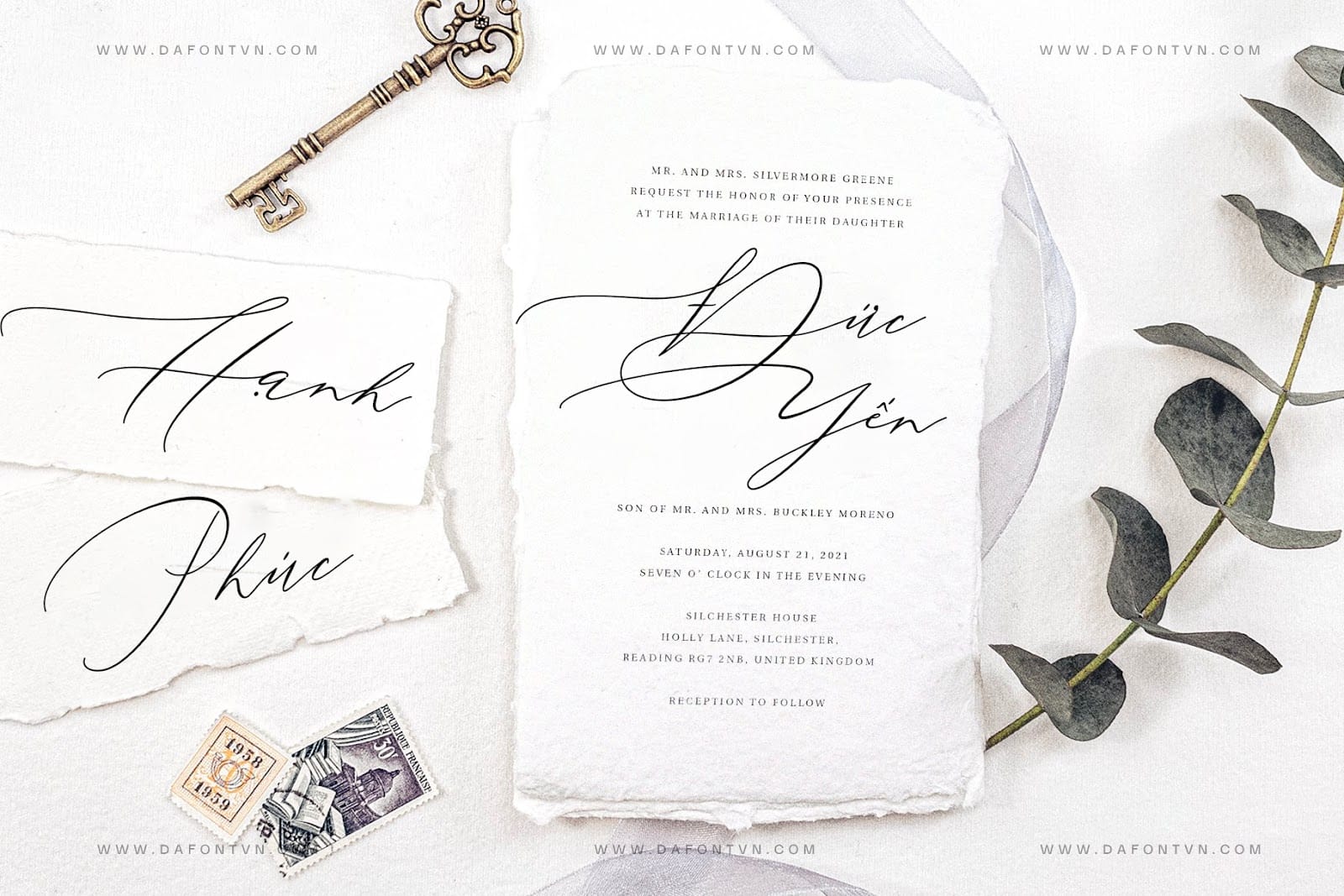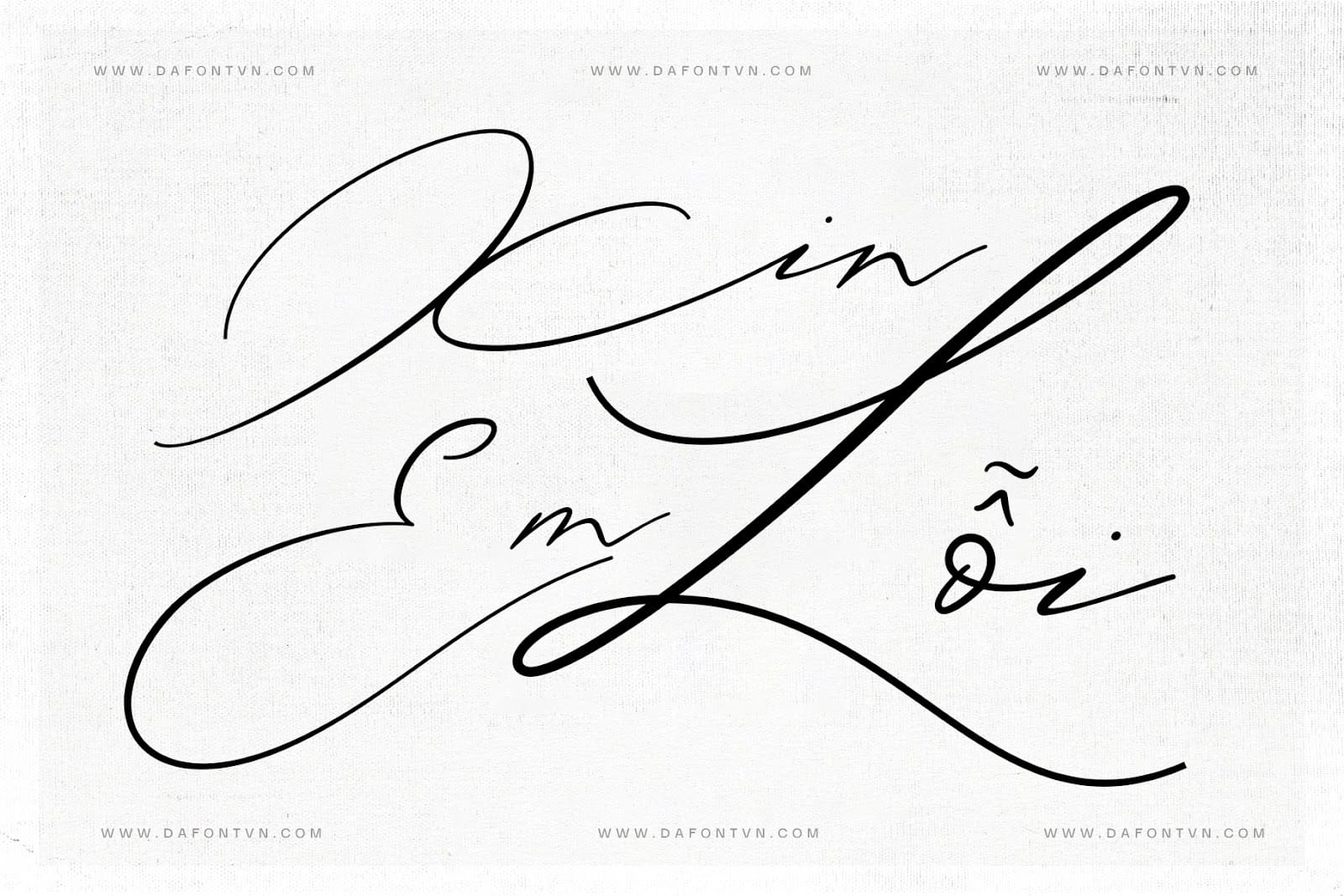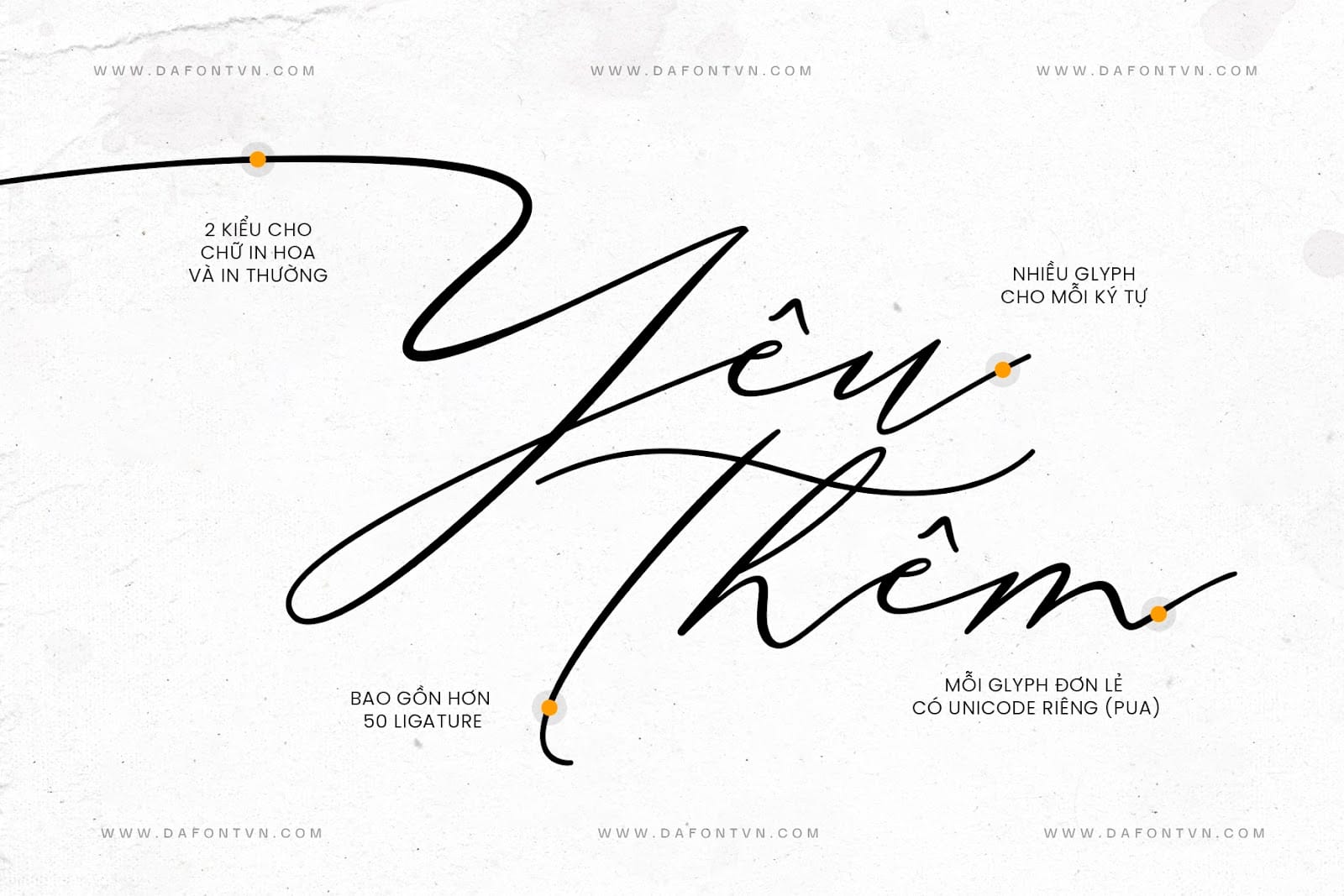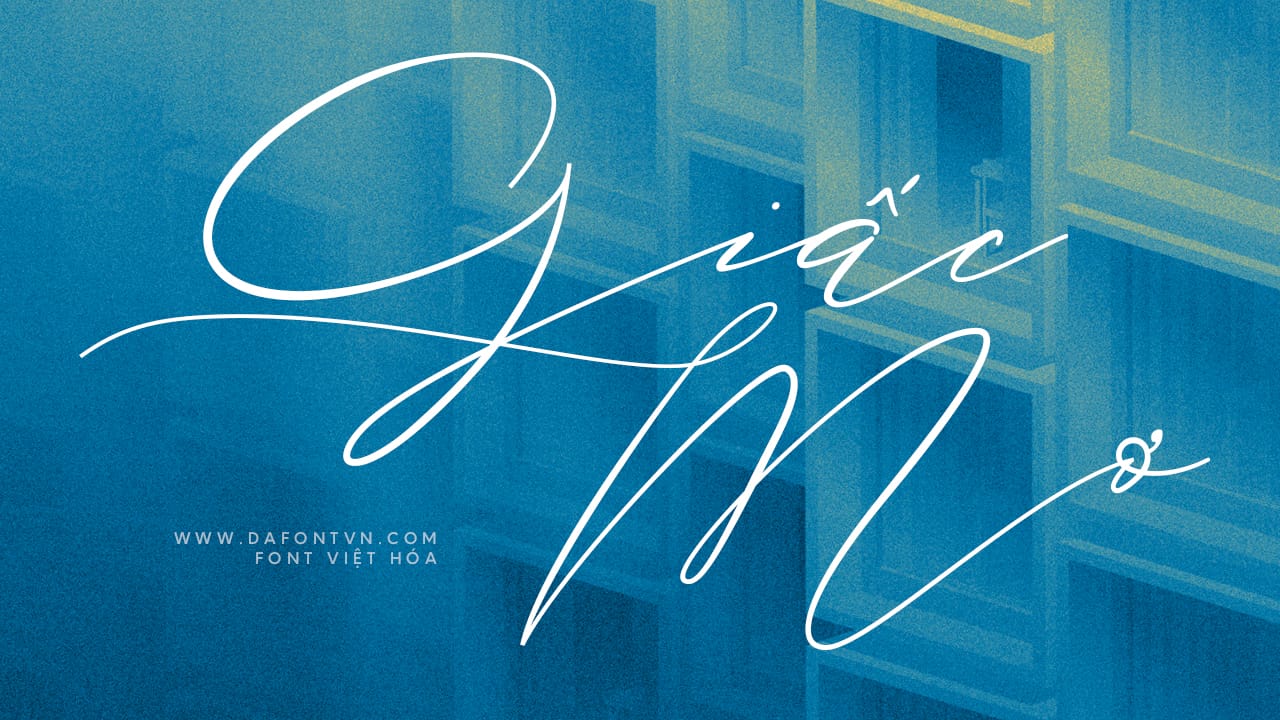
BP DolceVita là font chữ viết tay cực xinh xắn và hiện đại. Với các nét được vẽ thủ công chân thực mang đến cho bất kỳ dự án thiết kế nào cảm giác lãng mạn và thanh lịch.
Phông chữ này chứa hơn 800 glyph, bao gồm chữ hoa và chữ thường, dấu chấm câu, chữ số và 50 lựa chọn thay thế về kiểu chữ. Các ký tự được chia thành một số tính năng như Swash, Stylistic Sets, Stylistic Alternates và Contextual Alternates.
Nó được mã hóa PUA, có nghĩa là bạn có thể dễ dàng truy cập tất cả các ký tự của mình và sử dụng dễ dàng trên bất kỳ phần mềm hoặc ứng dụng nào bởi chúng mình đã tối ưu hóa.
Dolce Vita sẽ mang đến cho thiết kế của bạn một cảm giác mới về chữ viết tay hiện đại và đẹp mắt có thể sử dụng trong thiệp chúc mừng, thương hiệu, logo, thư mời, văn phòng phẩm, bao bì sản phẩm, tạp chí, bìa sách và nhiều hơn nữa.
Font BP DolceVita Việt hóa đầy đủ 2 kiểu (Regular và Bold), kerning, chỉnh sửa và tối ưu hóa lại font.